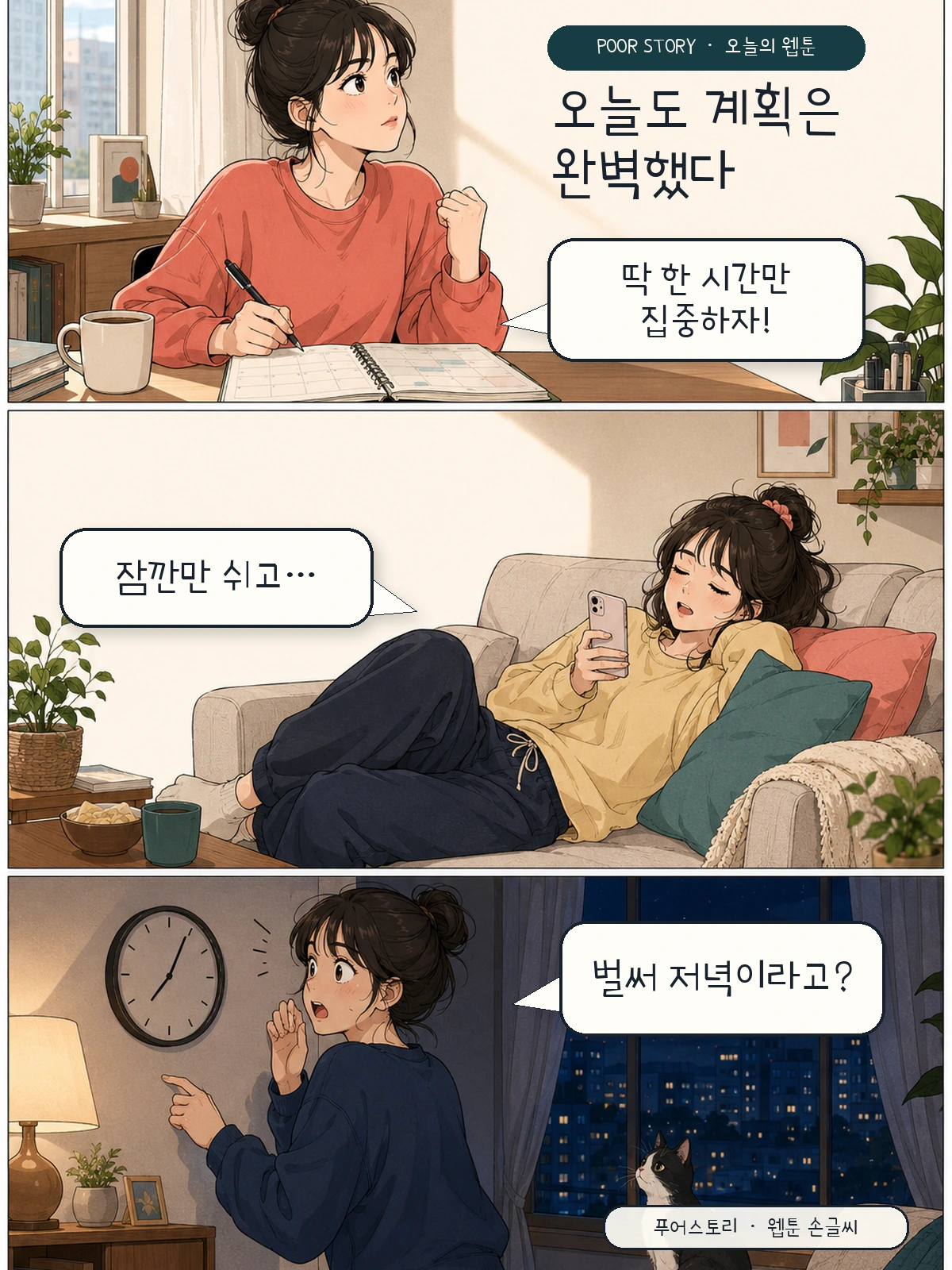
푸어스토리 — 윤디자인에서 배포하는 무료 폰트입니다. 수줍게 써 내려간 나의 이야기라는 뜻을 담아, 두근거림을 귀엽게 풀어낸 손글씨체
윤디자인이 만든 손글씨 서체로 2018년 구글폰트에 올라 있습니다. 폰트 파일 안에 적힌 한국어 이름은 서툰이야기입니다. 제작사가 영문 소개에 적어 둔 이야기가 이름과 이어집니다. 수줍게 써 내려간 나의 이야기가 있고 너를 볼 때마다 심장이 뛴다는 문장으로 시작해, 그 두근거림을 귀엽고 매력적인 형태로 옮겼다고 밝히고 있습니다.
조형에 대해 제작사가 남긴 구체적인 설명이 하나 있습니다. 초성마다 기울기 각도를 다르게 해서 고르지 않은 손글씨 느낌을 살렸다는 것입니다. 실제로 파일에서 재어 보면 받침이 붙을 때 글자가 0.2em 내려가는 탈네모틀이라, 기울기 차이와 높낮이 차이가 겹쳐 글줄이 손으로 쓴 것처럼 흔들립니다.
굵기는 하나뿐이라 위계를 만들 수 없습니다. 대신 손글씨체인데도 현대 한글 11,172자를 모두 담고 있어서 어떤 글자를 넣어도 네모로 빠지지 않습니다. 같은 윤디자인의 독도체가 2,484자인 것과 비교하면 실무에서 안심하고 쓸 수 있는 쪽입니다. 다이어리나 편지처럼 감성적인 짧은 문장에 어울립니다.